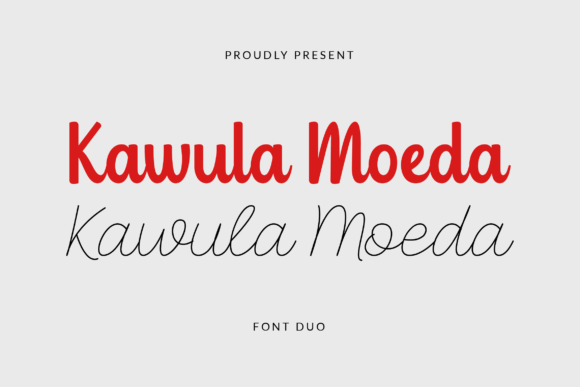
Kawula Moeda Font – Download Grátis
A Kawula Moeda é uma fonte escrita a mão que traz elegância e encanto ao seu design digital. Suas letras são delicadas e bem equilibradas, criando um padrão harmonioso que se adapta perfeitamente a múltiplas aplicações gráficas. Ideal para adicionar um toque delicado em logotipos ou criação de materiais educacionais, a Kawula Moeda é uma escolha perfeita tanto para quem busca uma fonte minimalista quanto para aqueles que desejam personalizar e tornar seus trabalhos ainda mais únicos. Seja para criar um projeto de revistas infantis, editoriais de moda ou até mesmo aplicativos educacionais, a Kawula Moeda oferece o charme cuidadosamente projetado necessário para capturar os olhares que ela merece.